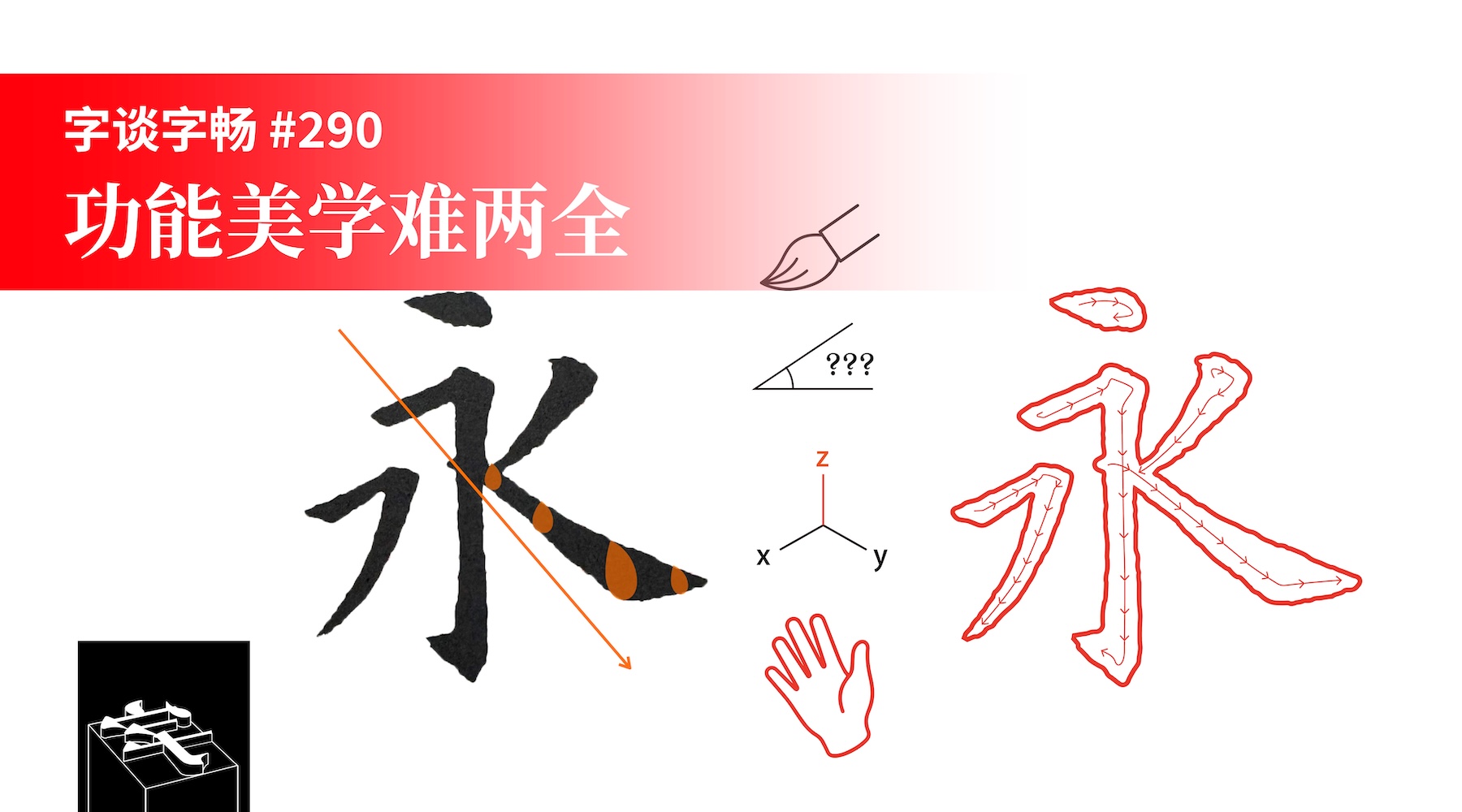
ATypI 2026 Stanford 系列访谈第六期,李少波老师与设计师林芳平将分享各自在大会上的演讲主题,在认知科学、视觉文化、功能、审美等多个交叉领域,为我们提供了研究及分析中文字体设计的视角。
- “Function is the foundation of type design”,李少波在 ATypI 2026 Stanford 的演讲
- 李少波曾主持国产大飞机驾驶舱显示字体设计项目
- 第七届方正奖中设立了「中国教科书体」的主题竞赛单元
- “Bridging Scripts: Communicating the Aesthetic of Hanzi to Latin-based Audiences”,林芳平在 ATypI 2026 Stanford 的演讲
- 激燃体,林芳平设计的中文字体,justfont 出品
- Nat McCully:毕业于芝加哥大学日本美术史专业。曾在 Apple、Adobe 推动日文正文排版相关的工作,主导 Adobe InDesign 日文版的工程开发;长期活跃于 W3C CSS 工作组,参与 W3C《日文排版需求》的编辑工作
- Inter-linguistic Typographic Harmonization,Nat McCully 在 ATypI 2026 Stanford 的演讲
- 李少波:湖南师范大学美术学院院长、教授、博士生导师
- 林芳平:平面设计师、字体设计师